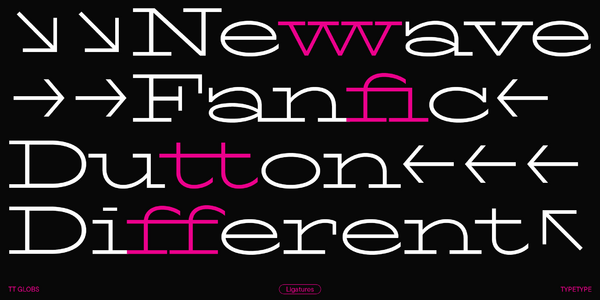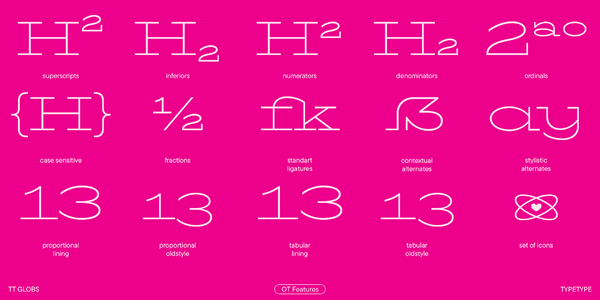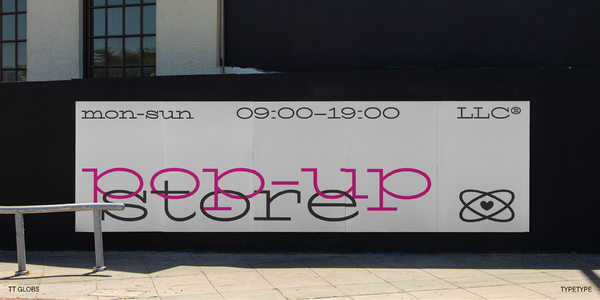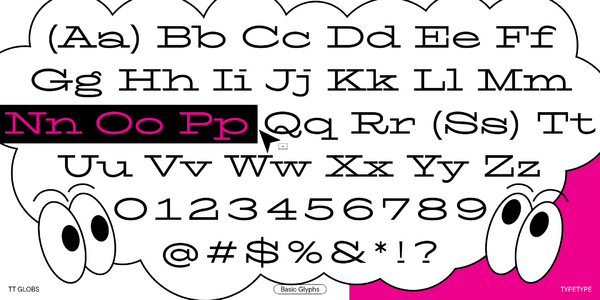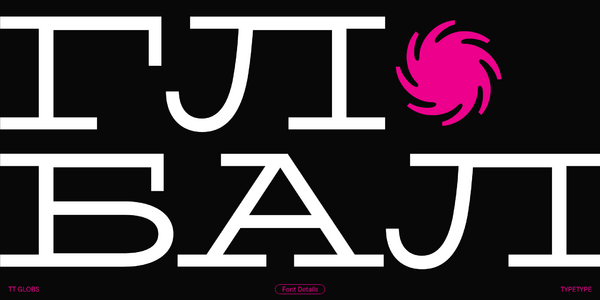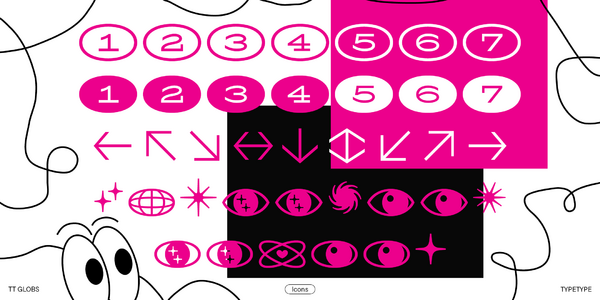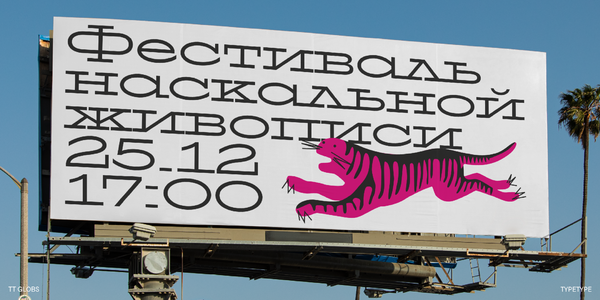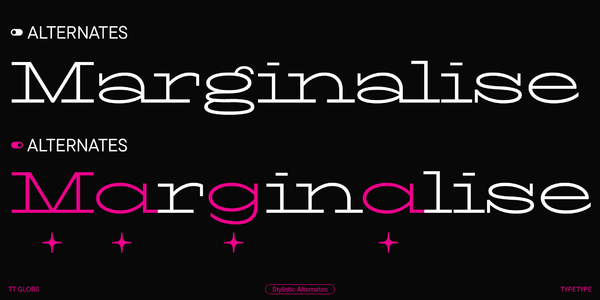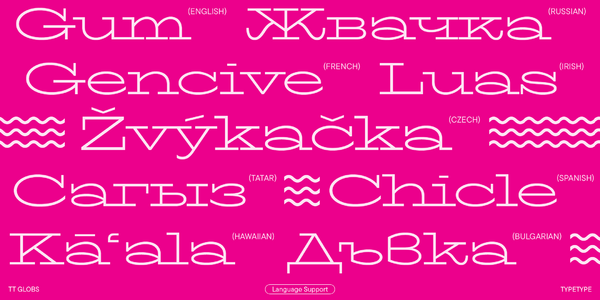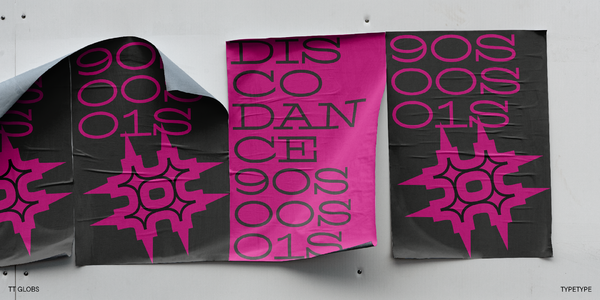
TT Globs
TT Globs — ТТ Глобс
Произносится «ТТ Глобс». «Globs» — производное слово от globe, в переводе с английского «земной шар». Буквы «TT» являются аббревиатурой названия компании.
TT Globs — стильный брусковый шрифт с широкими пропорциями, живым дружелюбным характером и «летним» настроением. Подойдёт для особых случаев.
Визуальной особенностью TT Globs являются длинные брусковые засечки
Благодаря длинным брусковым засечкам и довольно узкому спейсингу, вы всегда будете получать уникальный и неповторимый текст. В зависимости от выбранных слов можно даже создавать определенные визуальные образы. Кроме того, TT Globs выделяется очень широкими пропорциями букв, высокими строчными знаками, длинными восходящими и нисходящими выносными элементами. Чтобы разнообразить жесткий ритм шрифта, мы создали асимметричные волнообразные «ноги» и «хвосты», а также плавные элементы в некоторых буквах.
Семейство состоит из 4 начертаний: 3 прямых и 1 вариативного
О гарнитуре TT Globs
Встречайте обновленный TT Globs — теперь с поддержкой кириллицы! Значительно расширили кассовый состав и функционал этого харизматичного шрифта.
TT Globs — стильный брусковый шрифт с широкими пропорциями, живым дружелюбным характером и «летним» настроением. Создавая его, мы постарались объединить исторические формы брусковых антикв с современными представлениями о том, каким должен быть шрифт. Так у нас получилась актуальная, свежая и необычная дизайнерская гарнитура.
Главная визуальная особенность TT Globs — длинные засечки, которые в паре с
«растянутыми» пропорциями превращают набор текста в своеобразный паттерн. Интересно, что вертикальные засечки тоже довольно длинные — они подчеркивают закрытые формы знаков, придавая шрифту изюминку. Игривости шрифту добавляют асимметричные волнообразные «ноги» и «хвосты», а также плавные элементы в некоторых буквах. Некоторые знаки особенно интересно рассматривать: в частности, «Q», «R», «a», «s», «g», «ß» и другие.
В кириллическом наборе, который мы добавили в обновленную версию, TT Globs очень пластичен и выглядит необычно. Среди особенно интересных деталей — нестандартные «ноги» у «К», «Ж», «Я» и акцидентные клюшки у «Л», любопытные формы букв «У», «б», «ф».
Также в обновленной гарнитуре мы значительно увеличили кассовый состав, полностью обновили кернинг и доработали хинтинг, добавили новые OpenType фичи. В частности, основной набор валют расширился и появился минускульный регистр, добавились дроби, цифры для нумераторов и денумераторов, минускульные цифры и новые стилистические сеты.
Это шрифт для особых случаев, который, впрочем, отлично впишется в любой «шрифтовой гардероб» и разнообразит более простые базовые варианты. Он сможет стать частью айдентики музыкального фестиваля, молодежного бренда одежды или ювелирных украшений, модного бара или выставки уличного искусства.
Обновленный TT Globs — это:
• 4 начертания: 3 прямых и 1 вариативный шрифт;
• 1051 знак в каждом начертании;
• 33 OpenType фичи, в том числе возможность менять некоторые знаки на альтернативные;
• Поддержка более 230 языков.
TT Globs — смелое решение для дизайнерских проектов!
Что изменилось в шрифте:
• Расширился кассовый состав: количество знаков увеличилось с 625 до 1051;
• Появились новые OpenType фичи: их количество выросло с 26 до 33;
• Появилась поддержка кириллицы;
• Количество поддерживаемых языков выросло со 170+ до 230+;
• Полностью обновился кернинг, доработан хинтинг;
• Расширился основной набор валют, а также появился минускульный регистр валют (включая табулярные валюты для обоих регистров) и валюты для Numr и Dnom регистров;
• Появились дроби;
• Появились цифры для нумераторов /денумераторов и других фич;
• Появились минускульные цифры;
• Появились новые стилистические сеты.
ss01 | Alternative Latin Q, R
ss02 | Alternative Latin a, g, y
ss04 | Alternative Latin K, M, W, X, k, m, w, x
ss11 | Alternative Cyrillic D, L